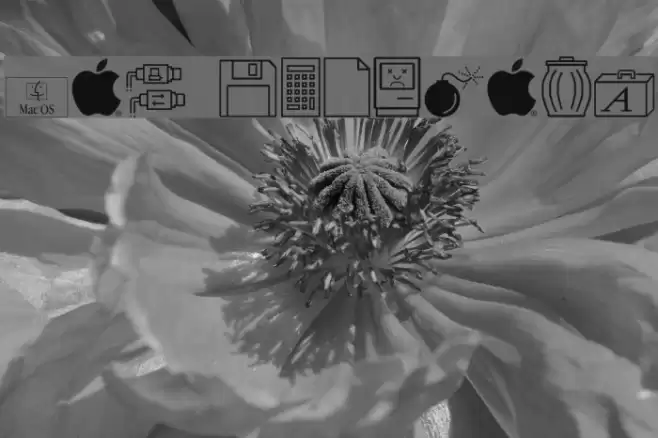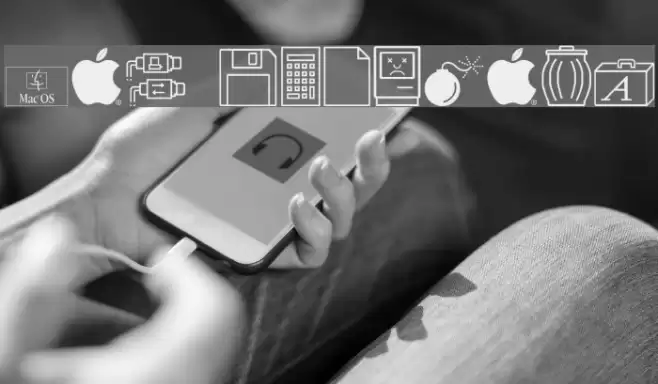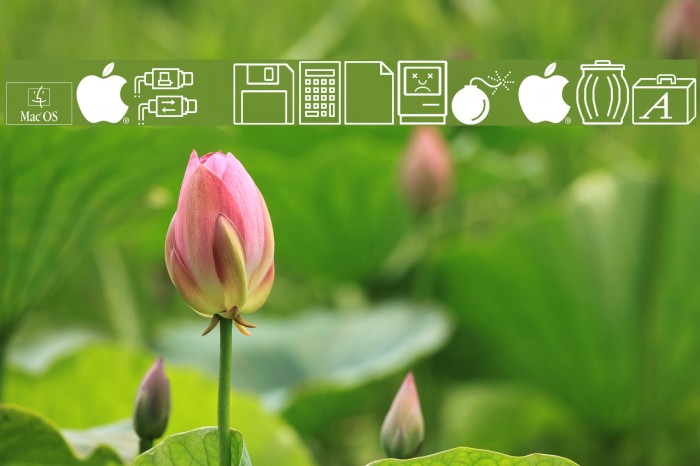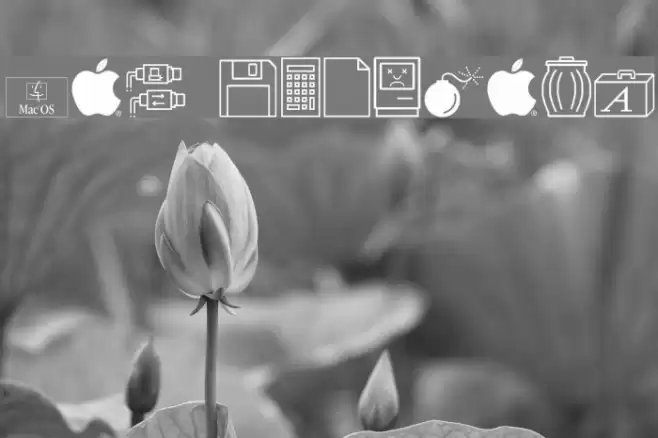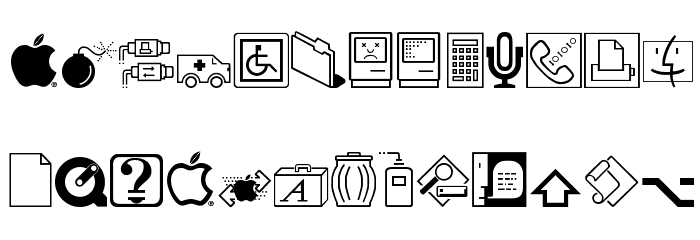
Mac Dingbats Font
| कंट्रास्ट | High |
| समग्र शैली | Vintage |
| उपयोग का मामला | Logos, Decorative elements, Digital interfaces |
| सुझाए गए प्रोजेक्ट | Ideal for retro-themed designs, digital interfaces, educational materials on computing history, or decorative elements in tech-related projects. |